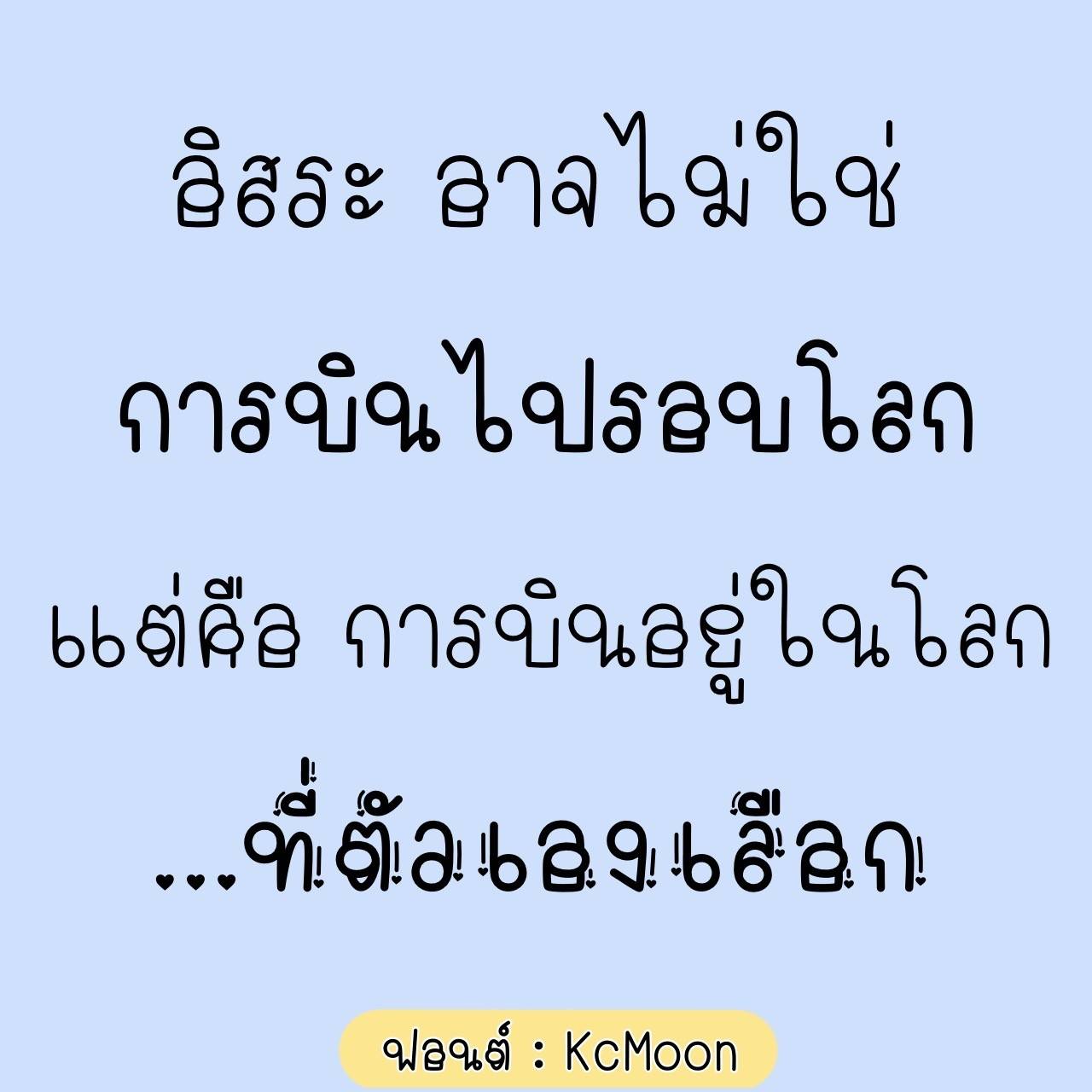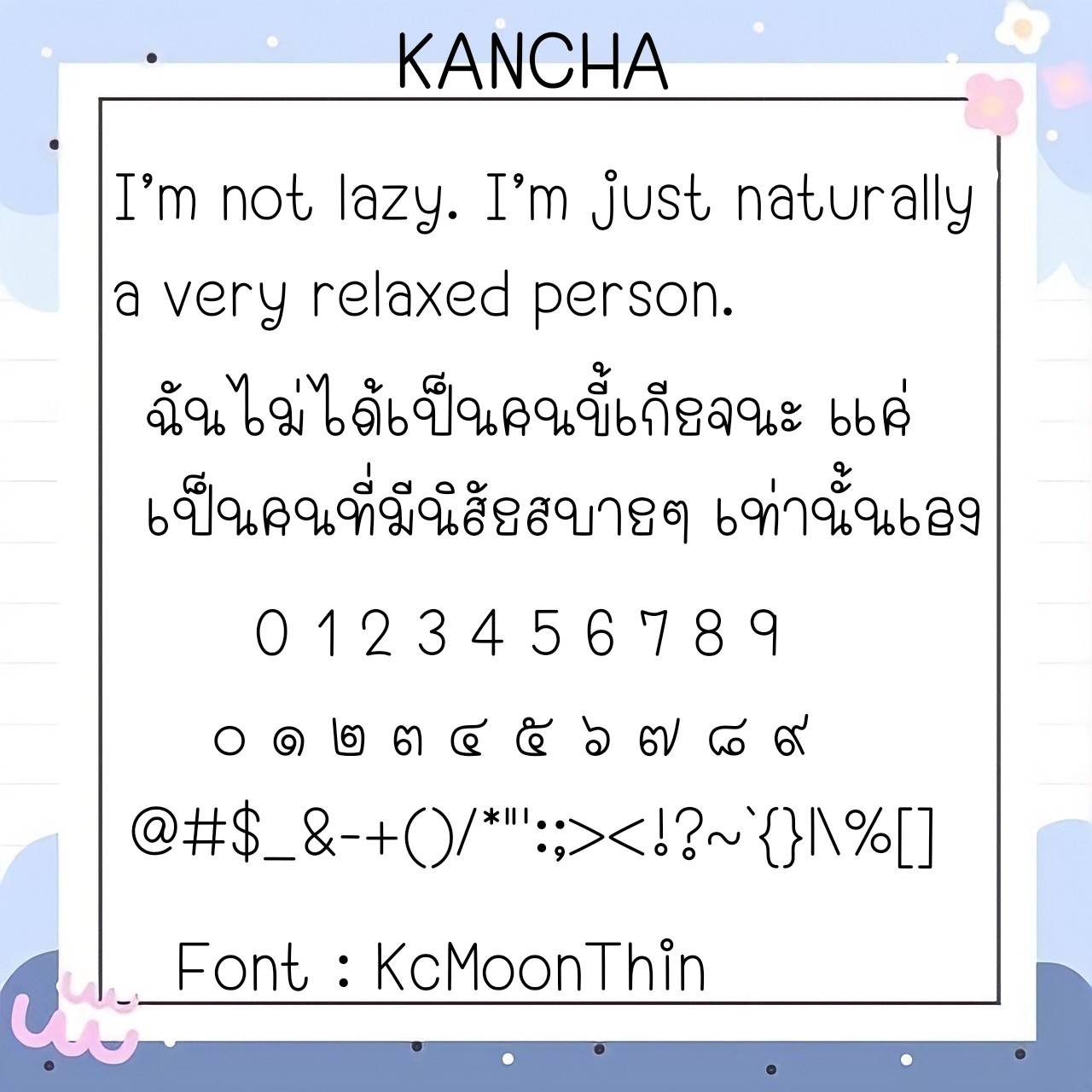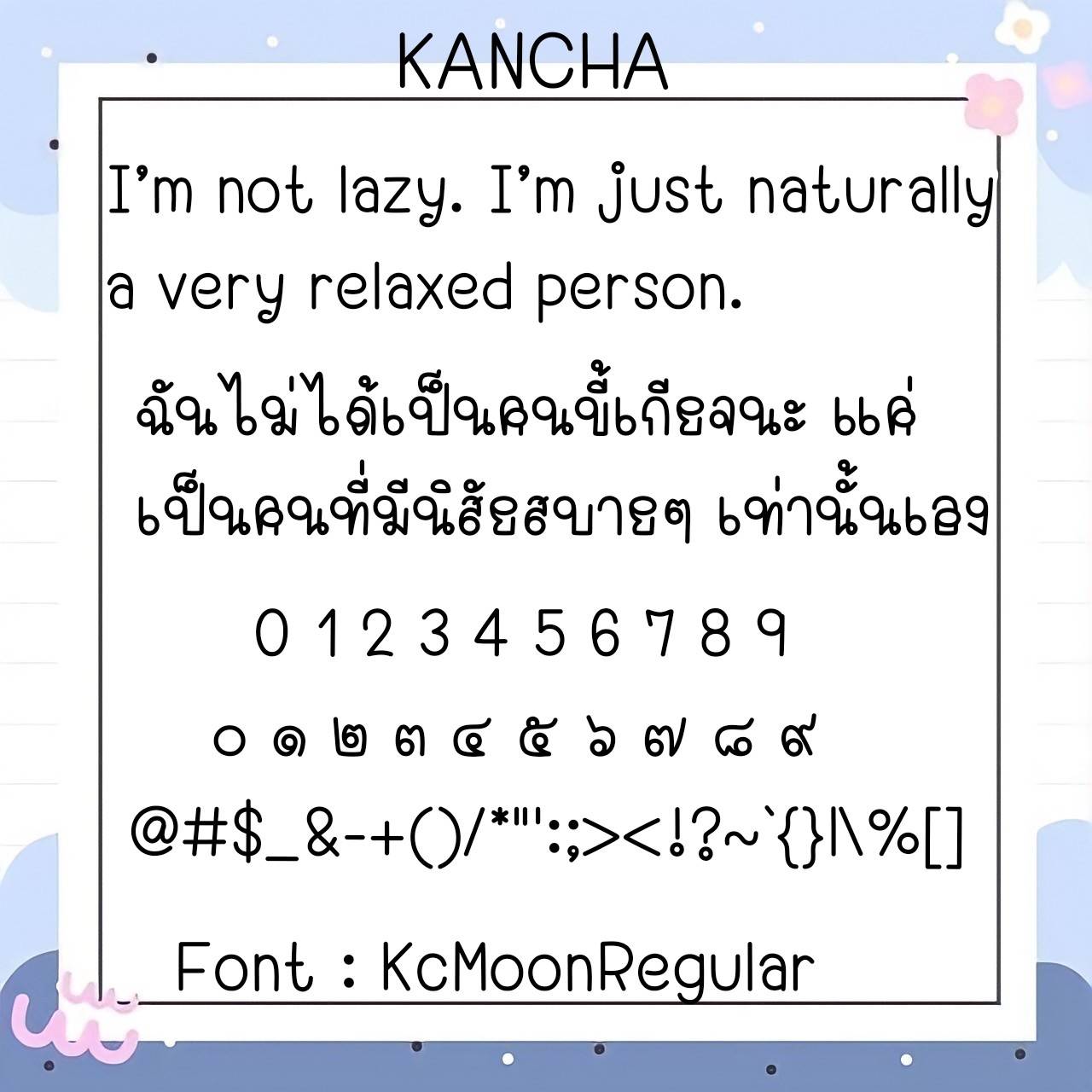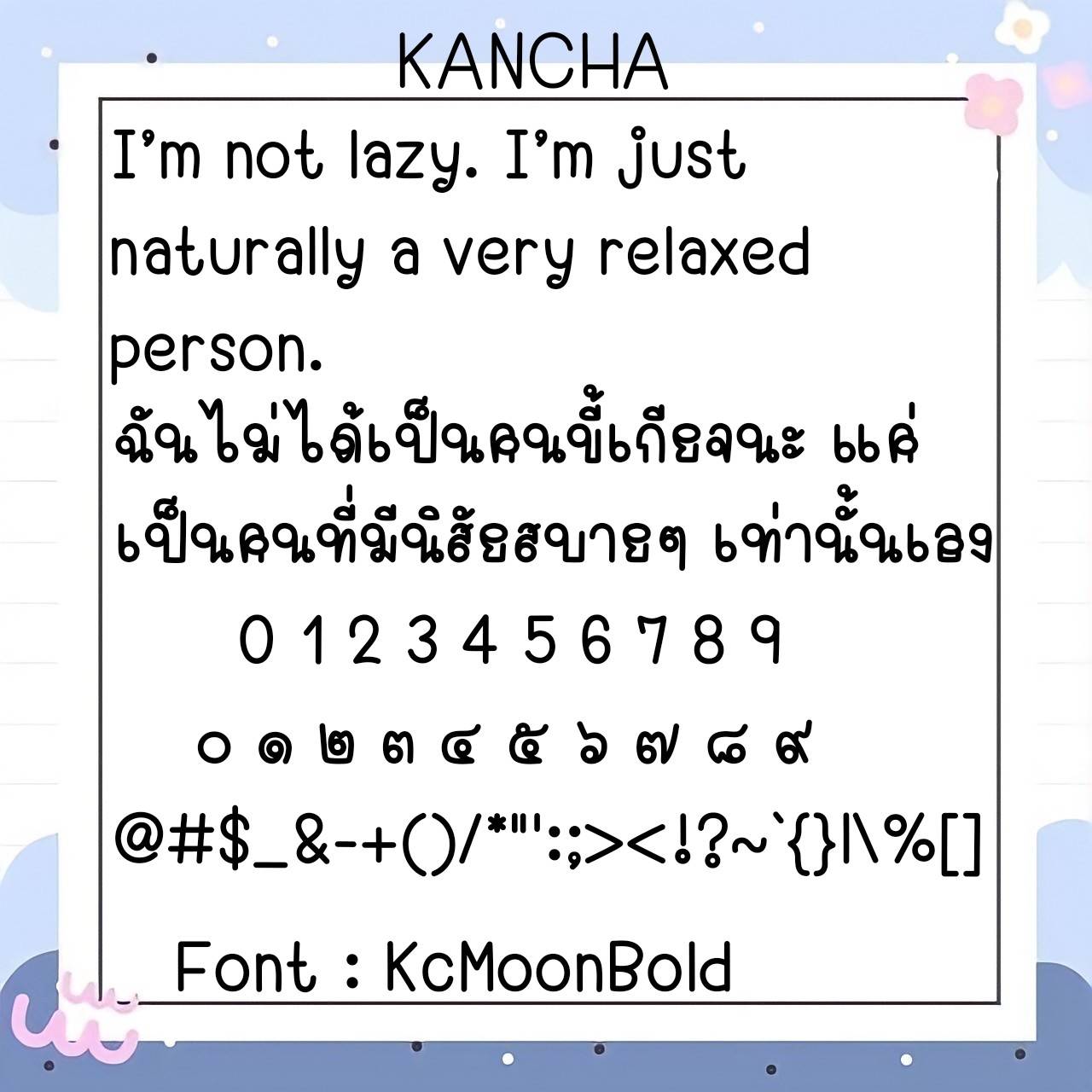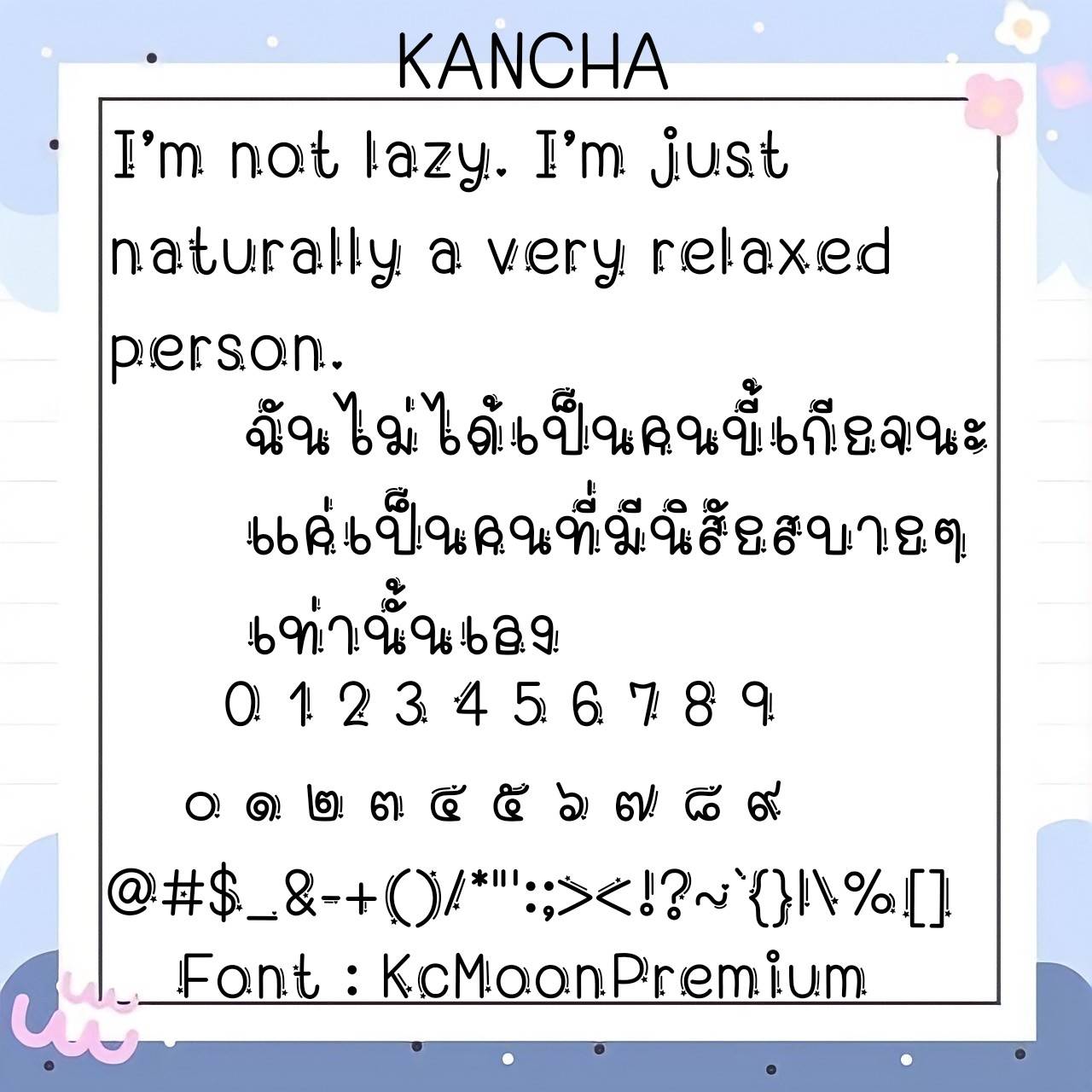
Font KcMoon
ชื่อสินค้า : Font KcMoon 💙
🔸ฟอนต์หัวโตอ่านง่าย แนววัยรุ่น มีความน่ารักในตัว ใช้งานได้สบายตา และมีตัวพรีเมียมเก๋ๆให้ในชุดอีกด้วยค่ะ🥰💙
🔹Big head font, easy to read, teenager style, with cuteness in itself Easy to use And there is a cool premium item in the set as well.🥰💙